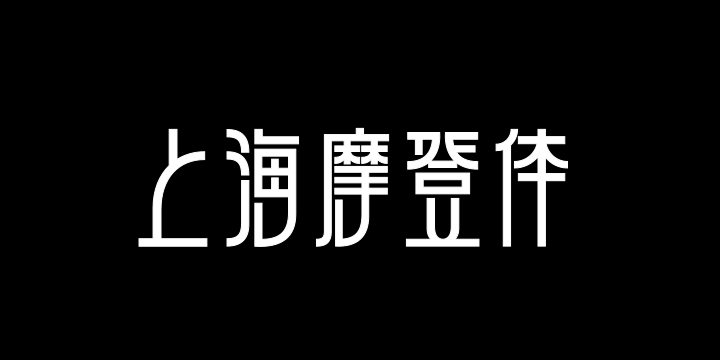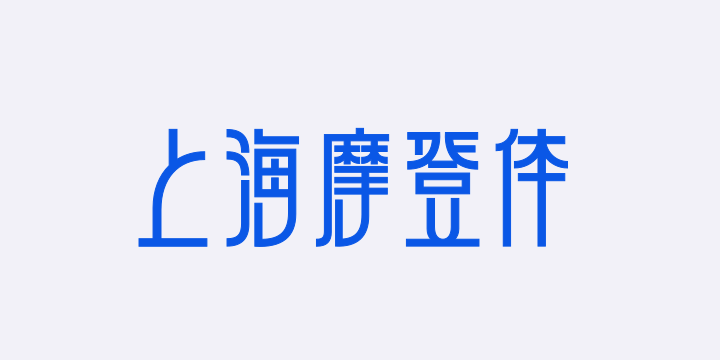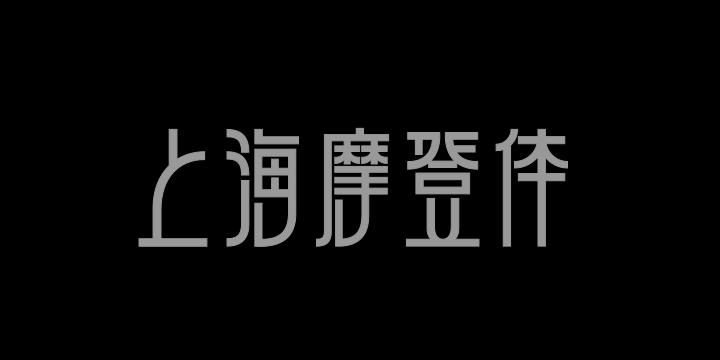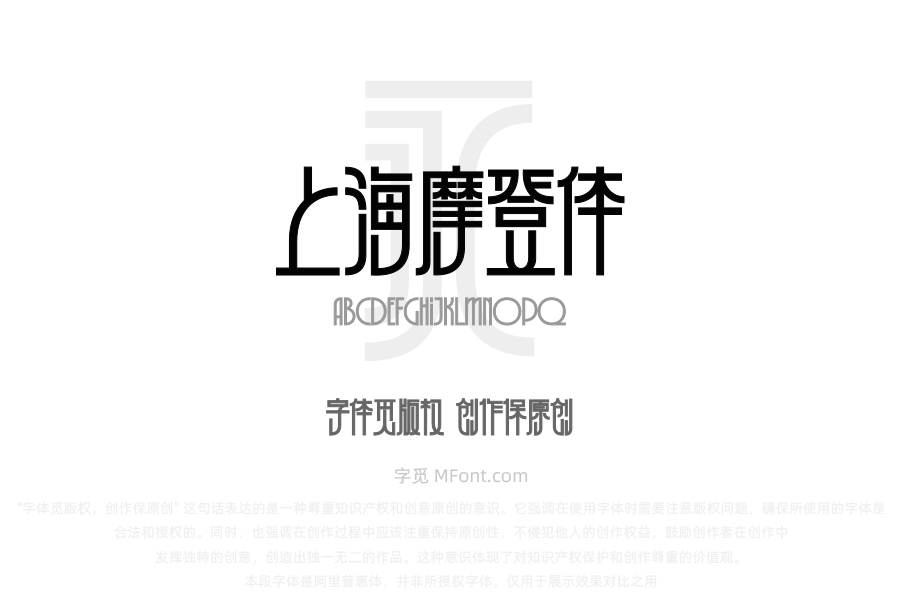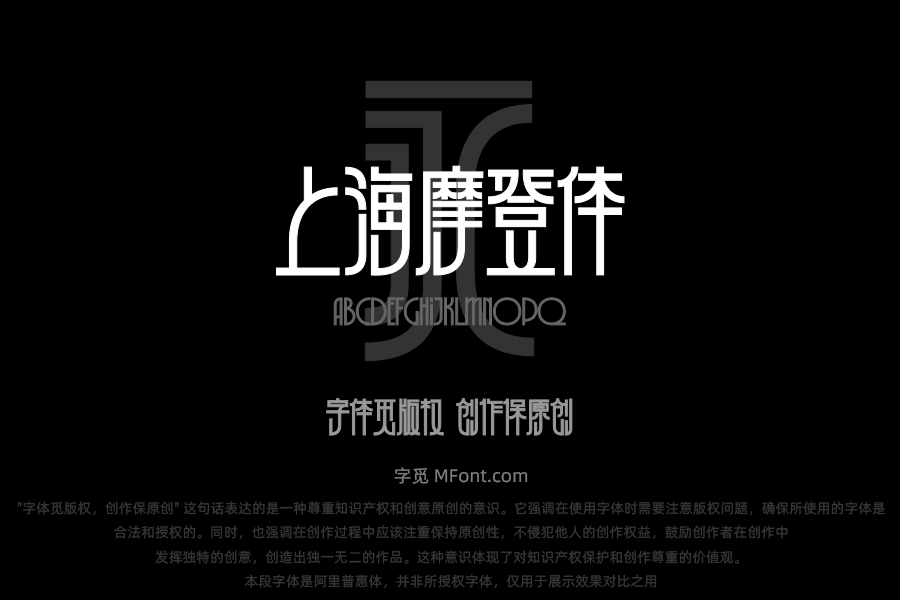
关于上海摩登体字体字库信息
字体全名: 上海摩登体
铸字厂: 茉莉字型
设计师: 茉莉字型
字体简介: 上海摩登体(Shanghai Modeng)是中国首个以城市文化为源流的中西文字体。字库按照GB2312国标标准研发。这款字体溯源了1930至40年代伴随着上海都市文化的起源与涌现,影响与遍及了各种视觉文化形态的装饰艺术(Art Déco)运动。这款字体的设计不是对装饰艺术风格的形式复刻,而是在秉承装饰艺术运动融合多元文化与创新未来的时代精神的同时,通过独特的字形语言,向城市文明演进的过去、现在与未来的提问。